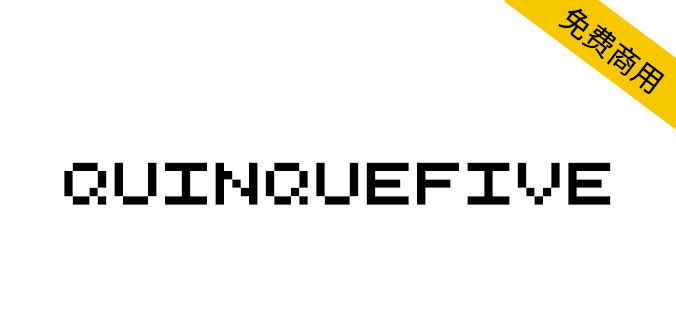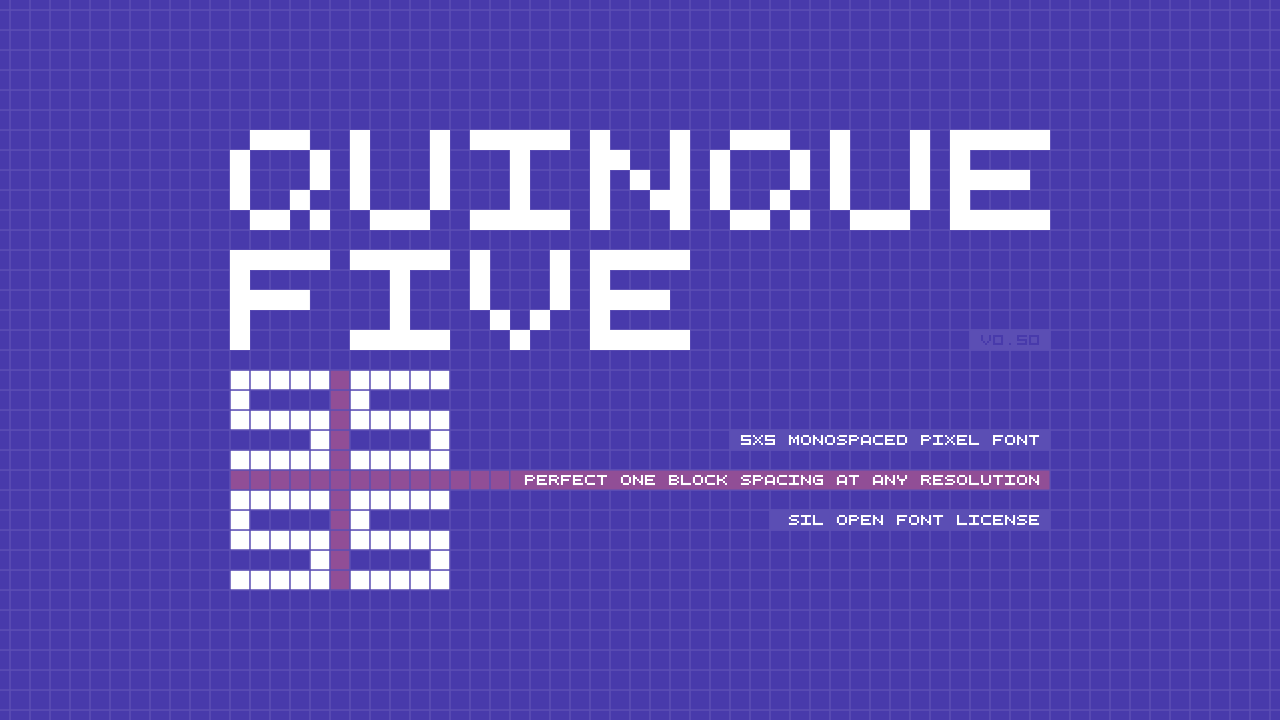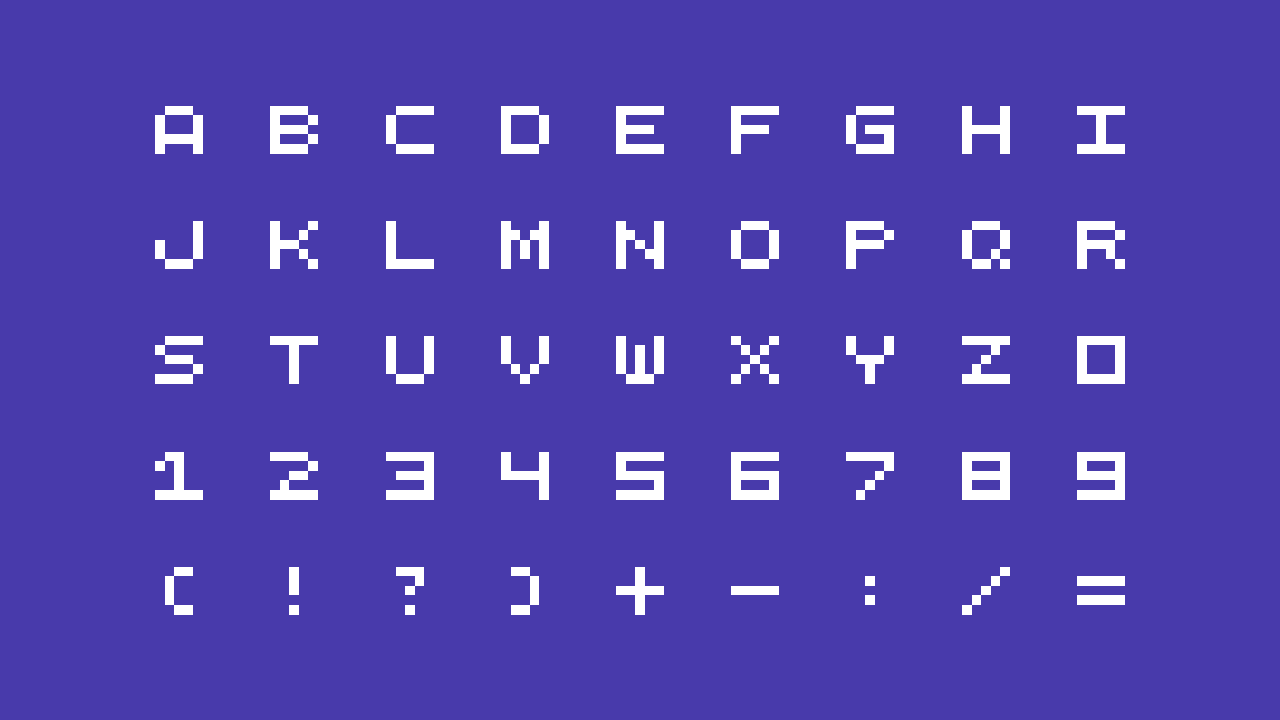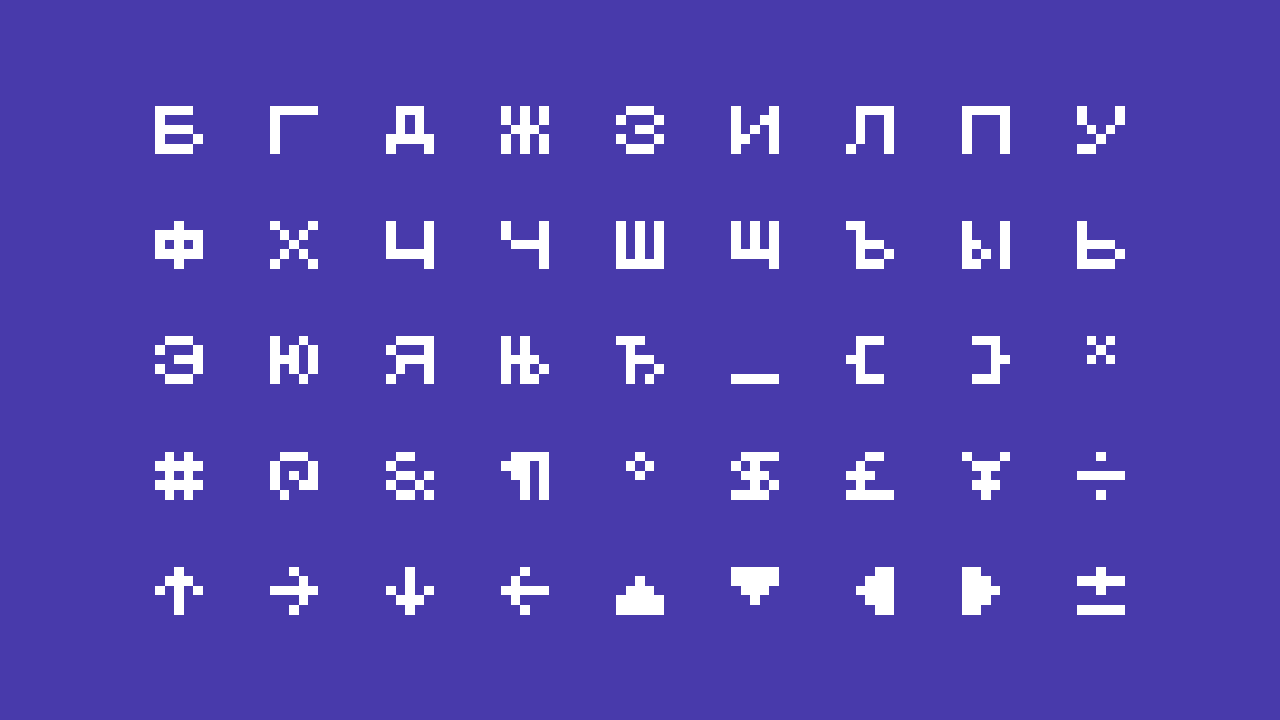
QuinqueFive一款根据SIL OFL协议发布的免费英文字体,5x5等宽像素字体, 字体包含 540 个字形。
推荐的字体设置:仅以 5px/4pt 的倍数使用它,并关闭抗锯齿。
支持 39 种语言(Asu、Bemba、Bena、波斯尼亚语、保加利亚语、车臣语、Chiga、康沃尔语、英语、Gusii、印度尼西亚语、Kalenjin、Kinyarwanda、Luyia、Machame、Makhuwa-Meetto、Makonde、Morisyen、North Ndebele、Nyankole、Oromo、Rombo、Rundi 、俄语、卢瓦语、桑布鲁语、桑古语、塞尔维亚语、香巴拉语、绍纳语、索加语、索马里语、斯瓦希里语、泰塔语、特索语、乌兹别克语(拉丁语)、文乔语、祖鲁语。)